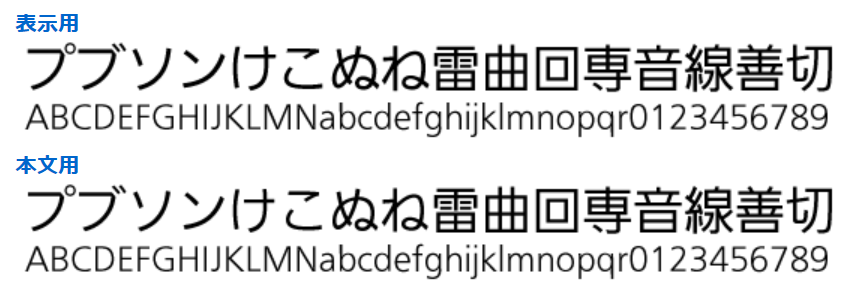
イワタUDフォント
「イワタUDフォント」はユニバーサルデザイン(UD)の視点に基づいて開発されたフォント。
UDとは年齢・性別や障害に関係なく、あらゆる人が商品・サービス・住居・施設を快適に利用できるように配慮されたデザインのことで、イワタではこうしたUDの視点にもとづいた文字デザインを詳細に調査・検討し、より幅広い用途で、正確な情報の伝達に対応している。2006年から販売が開始された。
「イワタUDフォント」は読みやすく、誤読されにくいという基本コンセプトのもと4つの観点「視認性」「判読性」「デザイン性」「可読性」から開発された。
視認性…文字ひとつひとつの構成要素を視認しやすくする
判読性…誤読しにくく、他の文字との判別をわかりやすくする
デザイン性…シンプルさ、美しさ、整理、整合性をもつ
可読性…文字列としての単語・文章の読みやすさ
イワタUDフォント(24書体)は「2009年度グッドデザイン・ライフスケープデザイン賞」(経済産業大臣賞)受賞している。
受賞の24書体はイワタUDゴシック表示用(L/R/RA/M/B/E/H)、イワタUDゴシック本文用(L/R/RA/M)、イワタUD丸ゴシック(L/R/M/B/E) 、イワタUD明朝(R/M/D) 、イワタUD明朝かなA(R/M/D) 、イワタUD新聞明朝 イワタUD新聞ゴシックとなる。
「イワタUDフォント」が2017年度グッドデザイン・ロングライフデザイン賞を受賞
株式会社イワタのUDフォント「UDゴシック、UD丸ゴシック、UD明朝、UD新聞明朝、UD新聞ゴシック」が2017年度グッドデザイン・ロングライフデザイン賞を受賞した。
この世界ではじめてのユニバーサルフォントは、 文字に新しい視点を与え、カテゴリーを創出させたという意味でもその意義は大きい。
高齢者や視覚障害者の方々が普段の生活を不足なく過ごせるかという当時の課題意識は、近年ますます重要性を増している。
新聞やパッケージの表示、ATM など、様々なコミュニケーションの接点で使われており、ユニバーサルフォントのもたらす価値を我々自身も知らず知らずのうちに享受している。
2017年「イワタUDフォント」(UD ゴシック、UD 丸ゴシック、UD 明朝、UD 新聞ゴシック)で受賞。
ユニバーサルデザイン(UD)視点の書体。年齢や性別や障害に関係なく、あらゆる人が商品/サービス/住居/施設を快適に利用できるように配慮されたデザインを採用。弱視、ディスクレシア(読み書き障害)ユーザーにもわかりやすく、小さく表示されても誤読されにくいほか、文字変形(長体など)をかけても視認性が良い。書体の美しさを保つ高いデザイン性も実現している。 電子・電気製品・OA機器の操作表示/交通標識/各種案内表示板/看板など、短い言葉を表示する際に使用でき、表示パネルなどに多い長体での使用にも適している「表示用」と、機器類の操作マニュアル/パソコン・ソフトウェア・Webの画面/薬品や食品類の服用・使用説明書/金融・保険の約款など、長い文章に使用でき、本文用としてかなの可読性を高めたデザインとした「本文用」を収録。 Adobe Japan 1-4(15444字)に準拠したPro版。